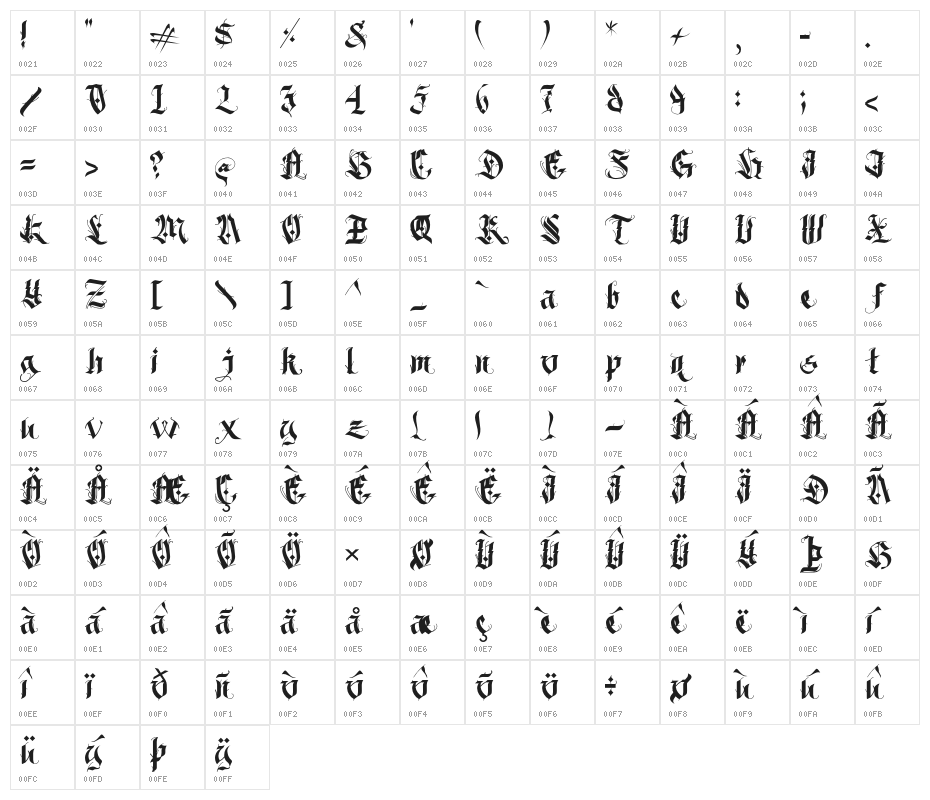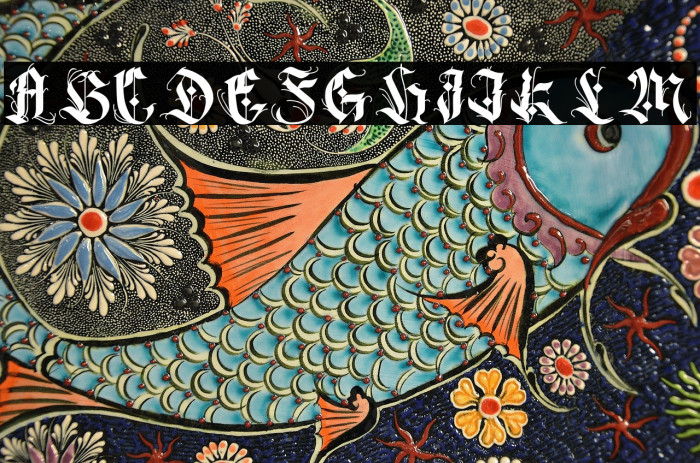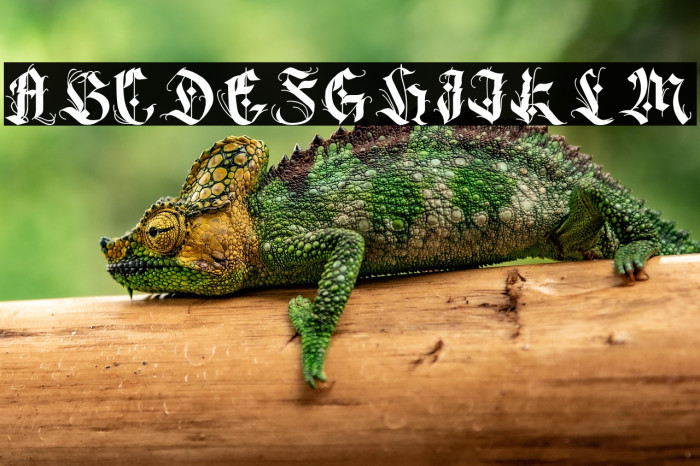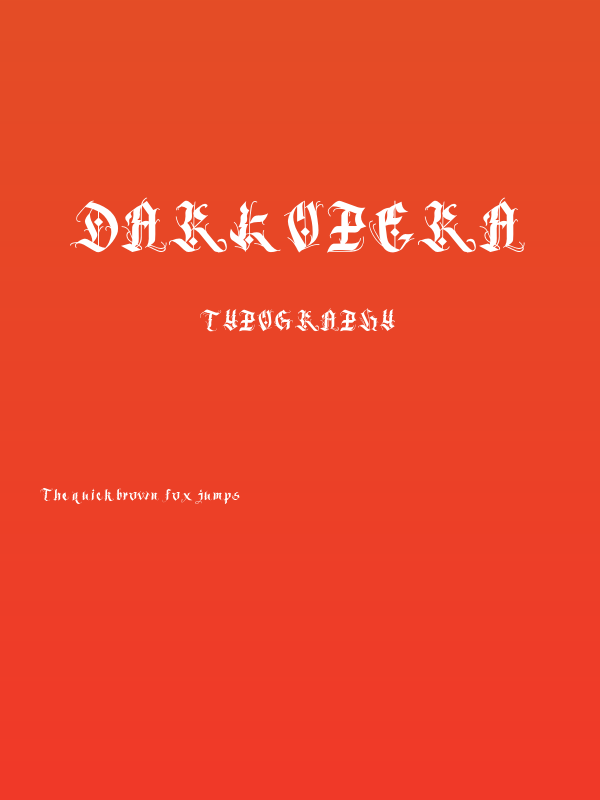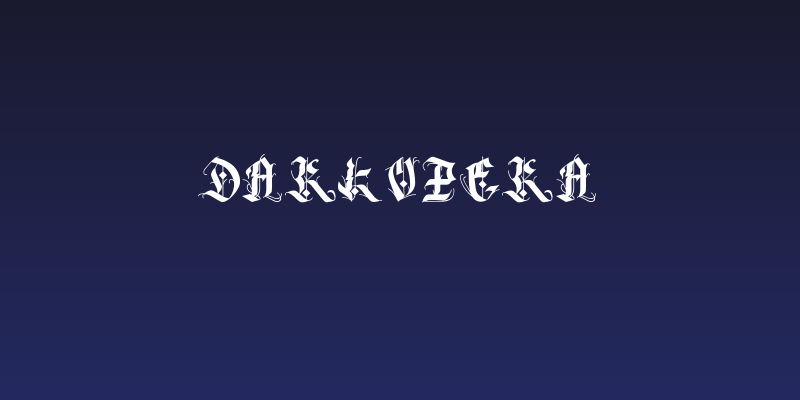
DarkOpera Font
| Categorías | Gothic |
| Estilo general | Gothic |
| Caso de uso | Headlines, Logos, Decorative purposes |
| Proyectos propuestos | Ideal for projects requiring a gothic or medieval theme, such as historical event posters, fantasy book covers, or themed invitations. |